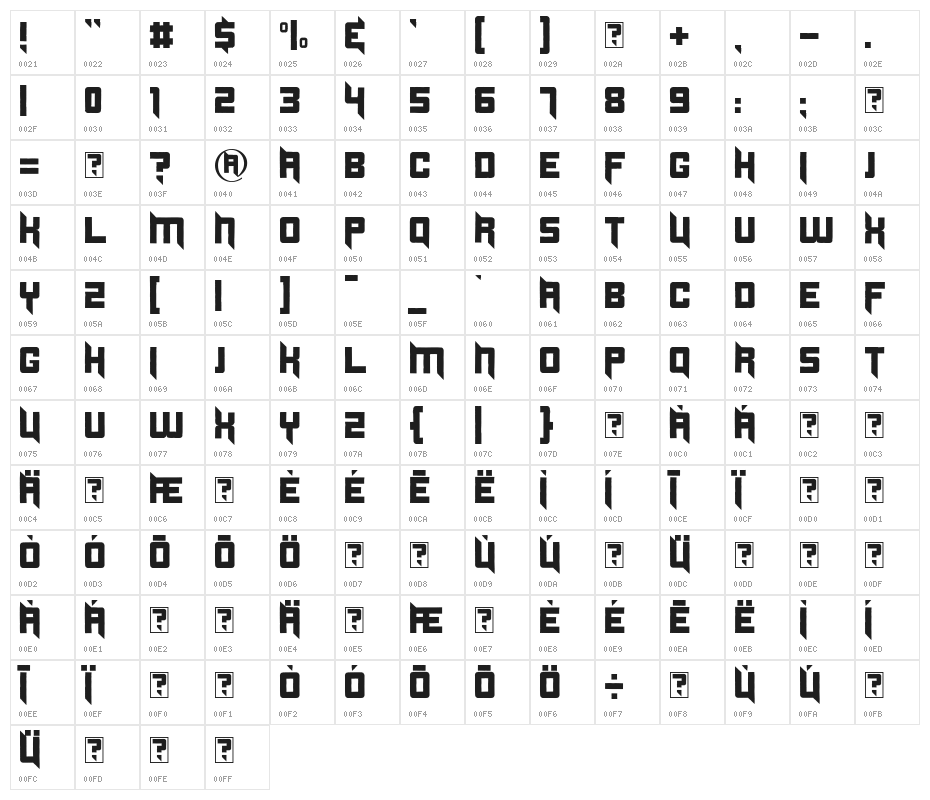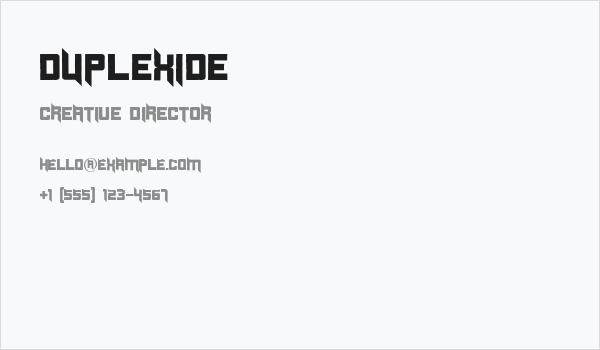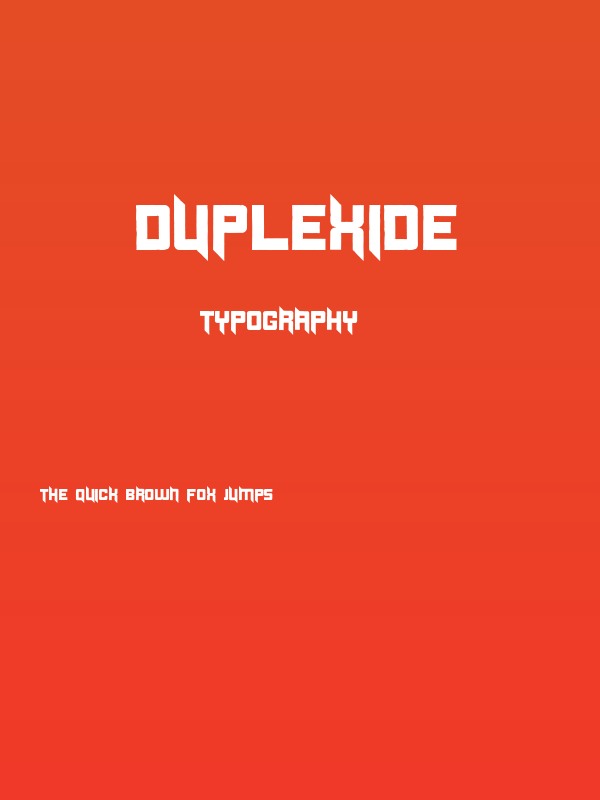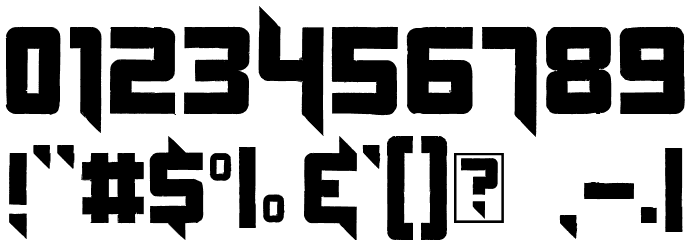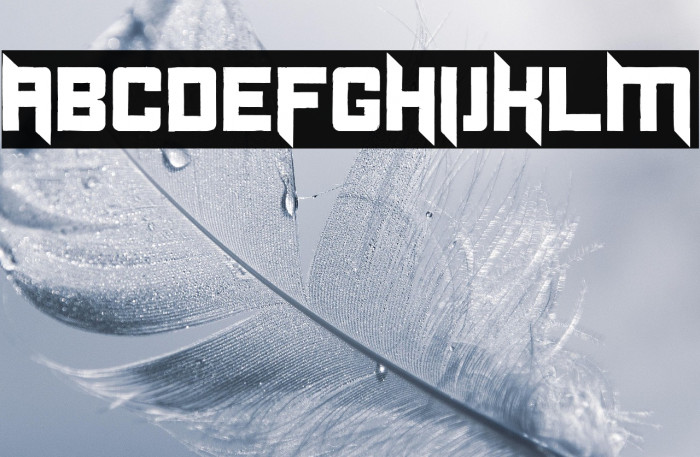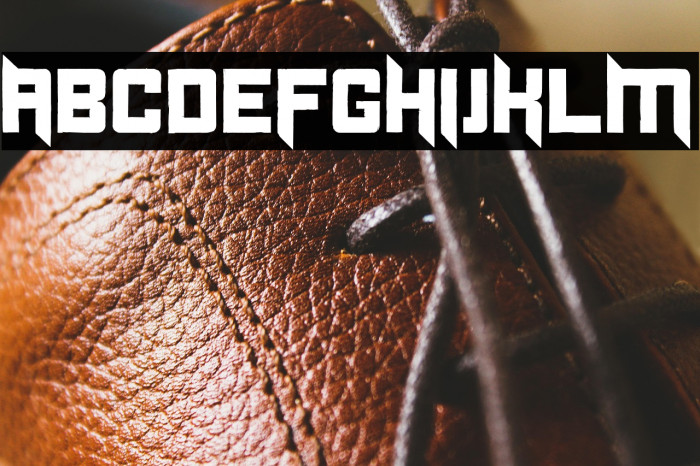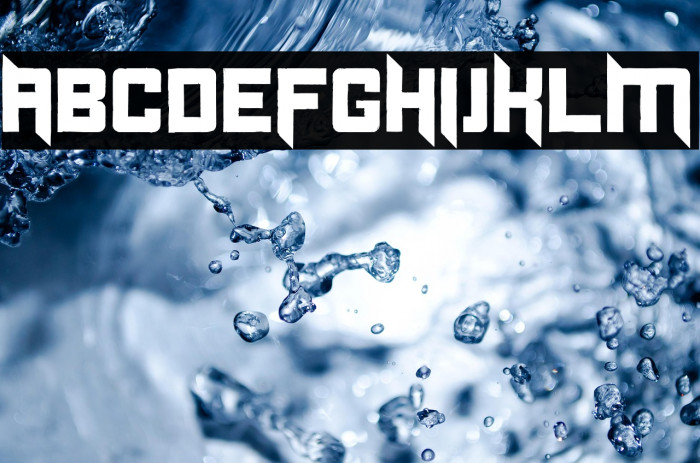
Duplexide Font
| Stile generale | Futuristic |
| Progetti proposti | Ideal for sci-fi themed projects, video game titles, posters, and branding that requires a modern and edgy look. |